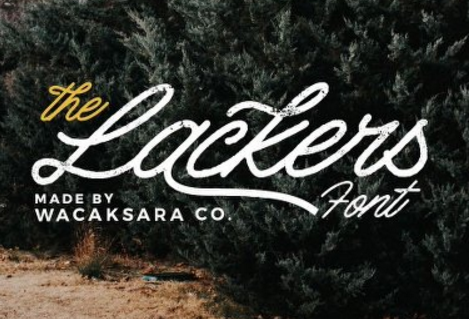
Lackers Script Font – Download Grátis
Lackers é uma nova fonte de estilo brush que recria um formato vintage com uma linha sólida, oferecendo uma fluidez natural. Ideal para projetos de marca pessoal, citações escritas a mão, design de móveis da casa, embalagens de produtos ou simplesmente como sobreposição de texto moderno e estiloso em qualquer imagem de fundo. Com três estilos de tipo script (Regular, Bold e Rough) e dois tipos de sans serif, Lackers oferece uma ampla gama de opções. Além disso, vem com maiúsculas e minúsculas, números e pontuações tanto no formato de script quanto na versão sans-serif, bem como muitas variações em cada caractere, incluindo alternativas do OpenType, ligaturas comuns e também swashes para personalizar seu design. Com sua proposta de qualidade e flexibilidade, Lackers é uma escolha perfeita para quem busca um estilo único que combine clássico com modernidade. Seja para projetos profissionais ou hobbies criativos, Lackers oferece a liberdade de criar designs únicos e vibrantes.